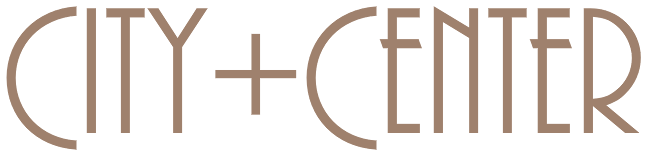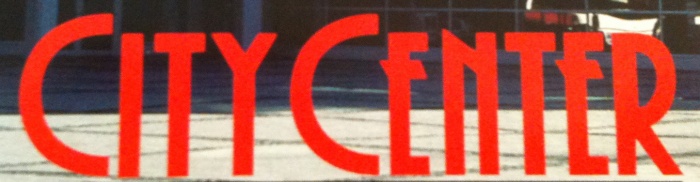
Schriftart des Markenzeichens vom CityCenter Dresden gesucht
Sehr nahe kommt die Plaza regular, aber sie passt nicht zu 100%. Ich habe auch schon nach ähnlichen Schriften gesucht (http://www.identifont.com/index.html), aber leider nichts passendes gefunden.
Hat jemand eine Idee? Oder einen Tipp, wo ich noch nach ähnlichen Fonts schauen könnte?
Naheliegend wäre ja, daß das aus der Plaza gebastelt wurde. Das wäre auch eine Erklärung für die ungleichmäßigen Strichstärken beim R.